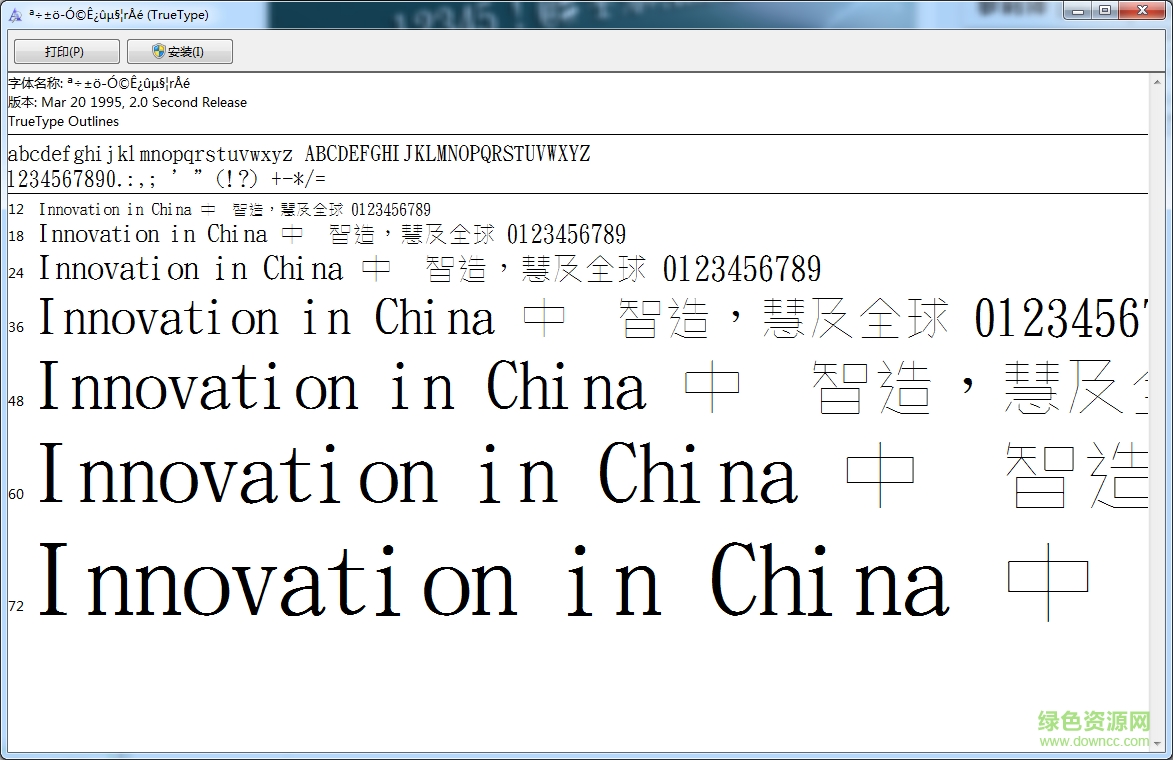
金梅個性鋼筆字體是金梅字體中別具一格的鋼筆字體,字體纖細簡單,極具個性使用廣泛,深受廣大用戶喜愛??靵砭G色資源網(wǎng)下載體驗吧!
金梅個性鋼筆字體是一款非常實用的電腦字體,該字體可應(yīng)用于鋼筆字設(shè)計方面,字體纖細大方得體,結(jié)構(gòu)端莊,可用于印刷出版、包裝設(shè)計、廣告設(shè)計、網(wǎng)頁設(shè)計、屏幕顯示等,喜歡的小伙伴趕緊下載體驗下吧~